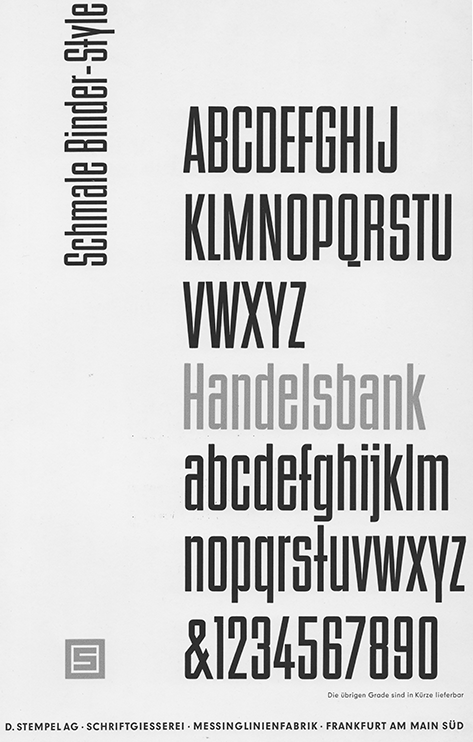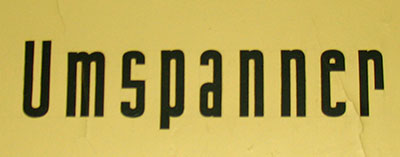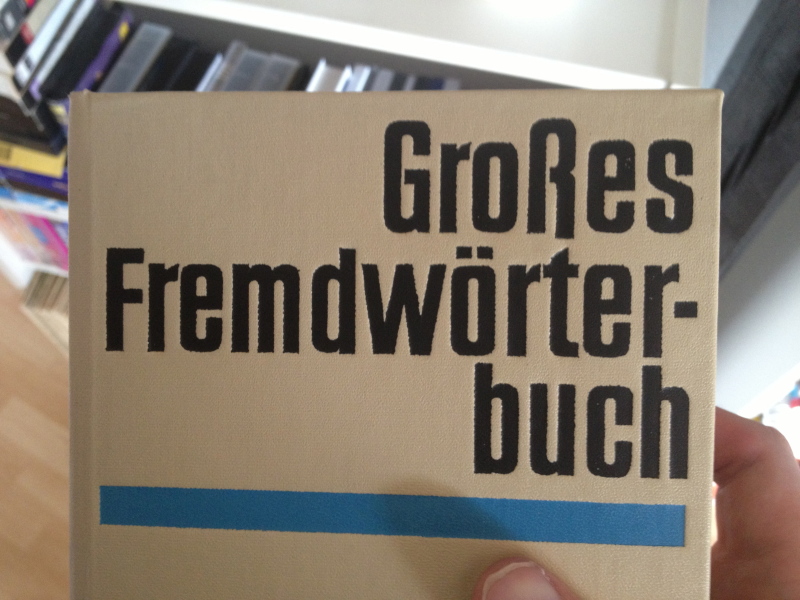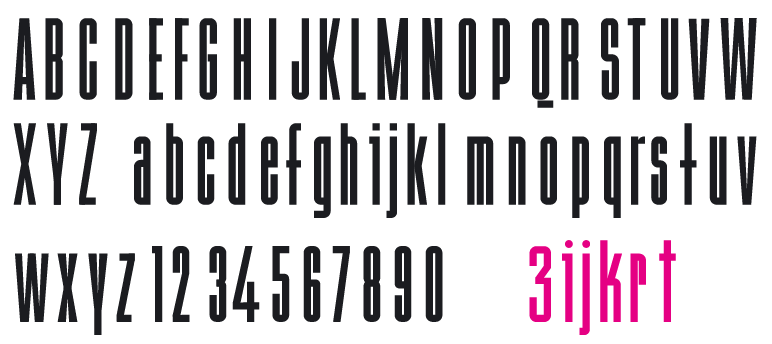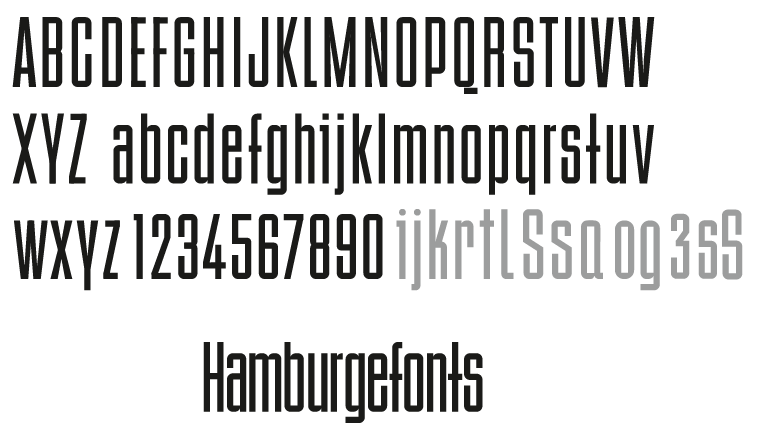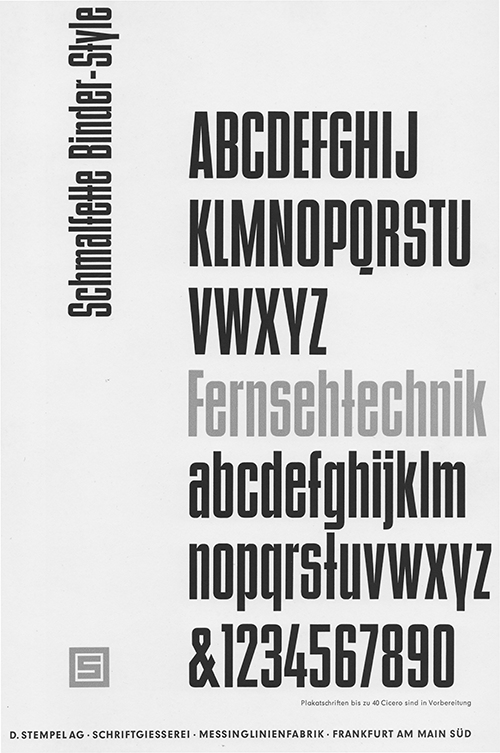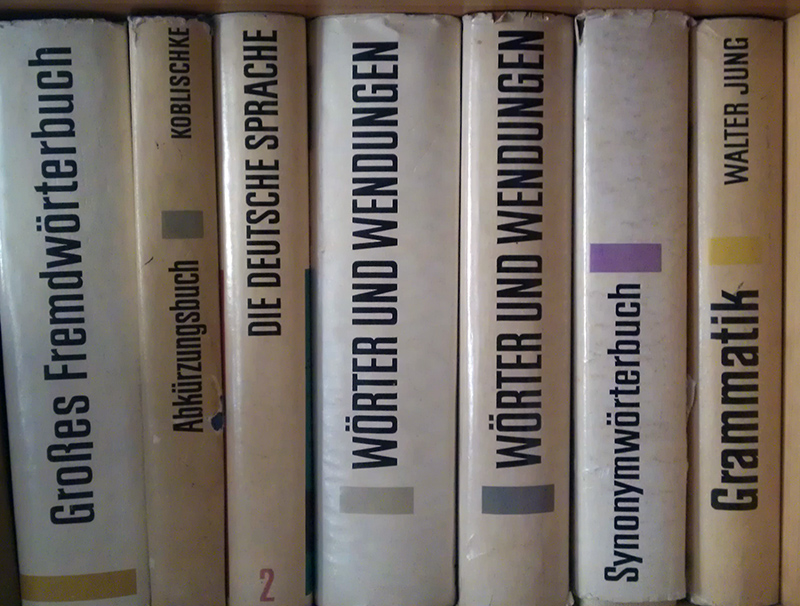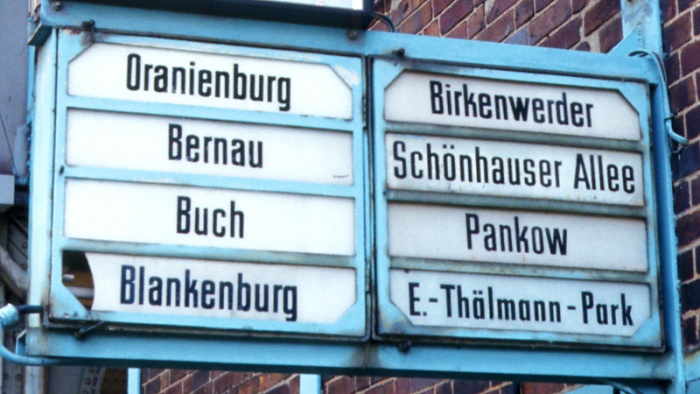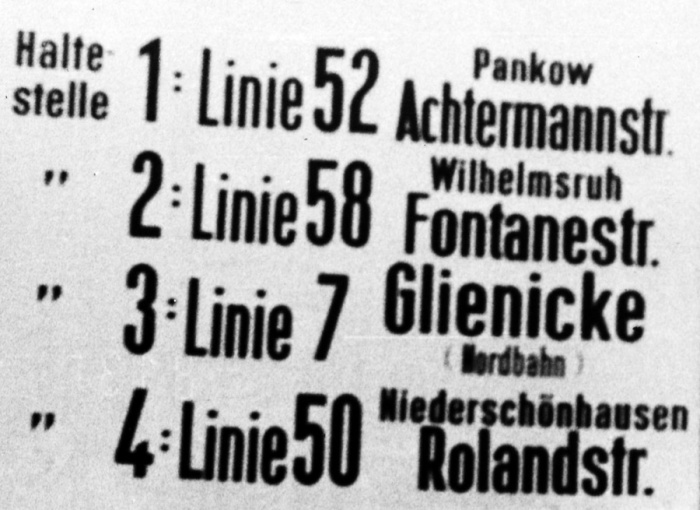
Und wieder wird eine Schrift gesucht (DDR??) ...
Das sind alberne Beispiele weil hier der zeitlich oder regional abgeschlossene »Raum« fehlt, der die Entwicklung entsprechender Assoziationen erlauben würde.
Nö. Die SB Garamont ist CI des Landes BaWü und wird hier sehr oft genutzt. BaWü ist räumlich klar abgegrenzt, zeitlich immerhin in eine Richtung. Aber die Zeit scheint gegen die Garamond zu sein, ihre Präsenz geht zurück. In Karlsruhe ist die Frutiger die die Hausschrift des KVV (Verkehrsverbund) und auch sehr viele Läden haben die Frutiger übernommen. Die Frutiger ist seit einigen Jahrzehnten in Karlsruhe omnipräsent und wesentlich häufiger als in einigen bis vielen anderen Regionen. Ich habe irgendwie Probleme mit diesen Zuordnungen als Bezeichner. Die DIN 1451 kann man als echte deutsche Schrift bezeichnen, aber danach wird es immer unschärfer.
Aber die gleichen Personen, die die Garamond und Frutiger in den genannten Zusammenhängen sehen, sehen die gleichen Schriften auch dauernd in anderen Kontexten. Es sind ja gängige Schriften. Die entsprechende Assoziation überträgt sich daher nur sehr schwach auf das Bundesland bzw. die Stadt.
(Sehr wohl kann die Frutiger aber z.B. aber für vielgereiste Leute zur Flughafenschrift werden, wenn man sie an 9 von 10 Flughäfen findet. Da ist der abgeschlossene Kontext wieder gegeben.)
Wie heißt denn diese Schrift von den Buchrücken?
Ich habe ja inzwischen die "Filmotype Glenlake" gefunden, da paßt aber u.a. wieder das kleine "a" nicht, weil es nicht nach oben abgeschrägt ist (wie auf den Buchrücken), sondern der obere Kringel rechts wieder nach unten abfällt (siehe "a" in Grammatik). Auch beim "G", "t" und "k" sieht man Unterschiede. Aber auf den ersten Blick wirkt sie doch recht ähnlich.
Wie heißt denn diese Schrift von den Buchrücken?
Ich habe ja inzwischen die "Filmotype Glenlake" gefunden, da paßt aber u.a. wieder das kleine "a" nicht, weil es nicht nach oben abgeschrägt ist (wie auf den Buchrücken), sondern der obere Kringel rechts wieder nach unten abfällt (siehe "a" in Grammatik). Auch beim "G", "t" und "k" sieht man Unterschiede. Aber auf den ersten Blick wirkt sie doch recht ähnlich.
Schick! Ich dachte da zuerst an die British Inserat. Bis auf das kleine k ist die sehr nah. Identifont spuckte aber nur den Link auf die British Inserat MN (2004) aus der Mechanorma Collection und nix zur Geschichte aus. Die MN-Version ist viel neuer als die Vorlagen. Google hat mich mit "British Inserat" auf gut Glück gleich auf eine Seite mit Download der kommerziellen British Inserat MN geschickt. Toll! Klauen ist leicht, aber Informationen sind Mangelware. Im alten Stulle Schriftenbuch habe ich eine Headline Massiv (Seite 149), auch sehr ähnlich ... Das kleine k erscheint mir aber eine Sonderausstattung zu sein. Aber damit habe ich immer noch keine weiteren Informationen über die Ursprünge der British Inserat, Vorläufer sowie alternative Versionen.
Wenn Ihr wüßtet, wie damals meistens Buchumschläge gemacht wurden, würdet Ihr gar nicht fragen, welche Schrift das ist ...
Es gab keine Setzerei, wo man sich als Grafiker mal ein paar Zeilen für Entwurf und Reinzeichnung setzen und ausdrucken lassen konnte, es sei denn man hatte private Beziehungen zu irgendeiner Privatklitsche.
In der Regel sammelten Grafiker Schriftmusterblätter und Schriftmusterbücher aus Antiquariaten, DDR-Druckereien oder ausm Westen (wenn man die Tante dort hatte), manchmal auch andere Bücher mit groß abgebildeten möglichst kompletten Zeichensätzen und fotografierten diese ab. Dann wurden die auf analogen Vergrößerungsgeräten - meist zuhause - auf Papier und in die Größe gebracht, mit einem Seziermesser geschnitten und mit Pinzette und Fixogum (sofern man an sowas rankam - wenn nicht dann eben mit normalen Fahrradschlauchkleber) fein säuberlich zu einer Reinzeichnung montiert, die dann von einer Reprokamera abfotografiert wurde ... Diese "Schriftbestände" wurden wie Goldstaub gewertschätzt und im Brandfall noch vor dem Parteibuch gerettet.
Die Schrift kann also aus den dubiosesten Quellen kommen, muß keine DDR-Produktion sein, war vielleicht auch nur ne Abreibeschrift (sowohl DDR- als auch Westproduktion) und kann sogar noch vom Grafiker beim Abfotografieren oder mittels Retusche bearbeitet worden sein ...
Es gab sogar einige Grafiker, die solche Schriftzüge selber gezeichnet haben ...
Ist heutzutage unvorstellbar, war aber bis zur Wende in allen mir bekannten Buchverlagen so.
Man hatte nicht viel Zeit zum Gestalten oder Ideen ausprobieren, weil die Entwurfs- und dann die Reinzeichnung mit erheblichen Zeit-, Nerven-, Beschaffungs- und Arbeitsaufwand verbunden war.
PS: Damals hat übrigens nie jemand gefragt, wo die Schrift herkommt ... das war immer bei Umschlägen oder Plakaten so - lange Texte hat man natürlich richtig gesetzt bzw. setzen lassen. Es gab sogar Grafiker, die deshalb einen Auftrag bekommen haben, weil man wußte, der "hat" die Times oder die Caslon oder gar was richtig Exotisches wie die Eckmann oder die Syntax ...
Na klar, wenn Dewag Signograph, Druckgenehmigungsnummer und EVP-Preis draufsteht, wäre es schwierig, das nicht als DDR-typisch wahrzunehmen — relativ unabhängig von der Typographie.
Die DDR-Assoziation stellt sich auch ohne diese Zusatzangaben ein. Das Schild hängt bei mir über der Haustür in ca. 2,50 m Höhe. Da kann niemand diesen sehr klein gesetzten Firelefanz mit DEWAG und EVP lesen. Trotzdem haben mehrere Besucher das Schild auf Anhieb als eben »altes DDR-Schild« identifiziert. Ich kann nur vermuten, dass es an der Schrift liegt, in der Bitte Tür schließen gesetzt ist.
Ich fand jetzt aber über etliche Querverweise die "Compressa", scheinbar ein Remake der "Neuen Steinschrift"?!?
Diese gefällt mir jdf. sehr gut. Das große S und das kleine c und einige andere Dinge fallen zwar sofort abweichend ins Auge, aber im großen und ganzen empfinde ich den optischen Gesamteindruck (z.B. von weitem betrachtet) als sehr ähnlich. Vor allem bei den Ziffern ...
(Was mir nicht so gefällt ist so auf den ersten Blick eine gewisse Ähnlichkeit zur DIN Engschrift. Aber naja ...)